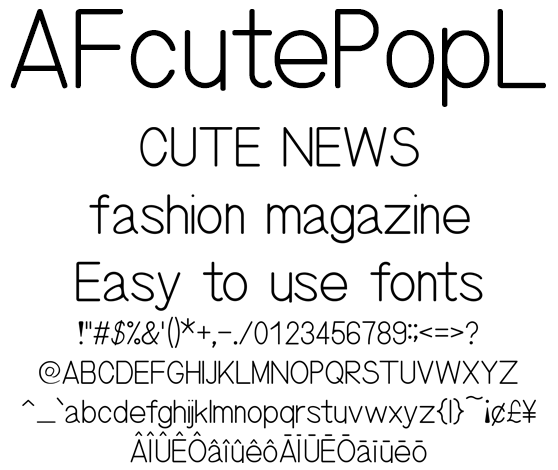
キュートな丸ゴシック欧文フォント AFcutePopL
AFcutePopL
とにかく目立つ丸ゴシックなライトウエイト欧文フォントは、キャッチな場面の同人系、コミック、アニメ、ゲームに最適。パンフレット、リーフレット、フライヤー、ファッション系コンテンツに使えるフォントです。日本のローマ字表記で使われる訓令式やヘボン式で扱う Ô や Ō を収録、人名地名へのアプローチもリアルです。
キュートな丸ゴシック欧文フォント AFcutePopL